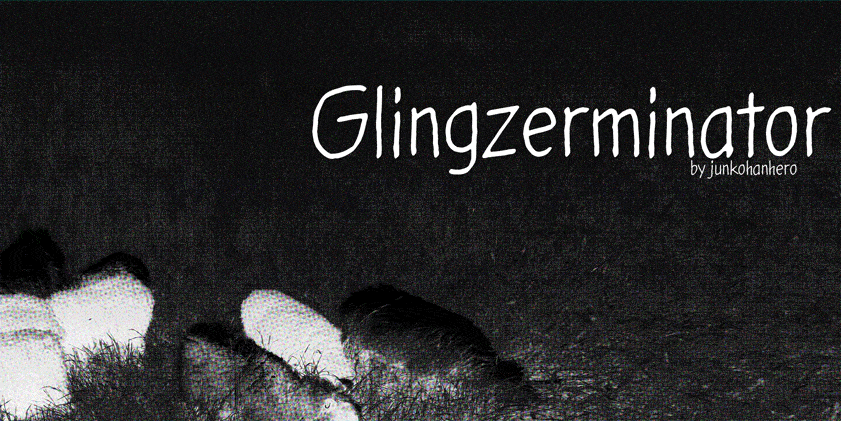
Glingzerminator Font
Aqui está uma versão em português do Brasil, envolvente e natural para a página de download da font “Glingzerminator”, escrita como se fosse um blog de recursos gráficos informativo: Nossa fonte Glingzerminator é um gênio brincalhão que não pode deixar sua sala de estar em paz. Especialmente criada para quem ama um pouco de humor nas páginas do seu projeto, essa fonte tem a capacidade única de fazer seu trabalho soar mais como uma divertida jogatina que um esforço sério. Se você está procurando por algo com o qual criar designs alegres e cheios de vida sem abrir mão de sua privacidade ou ser obrigado a pagar por isso, então Glingzerminator é definitivamente para você. É totalmente grátis para uso pessoal; só precisamos de um pouco mais de seu tempo para manter suas páginas engraçadas e coloridas. O designer Hamilton criou uma fonte que brinca com letras e ideias, transformando cada página em um divertido desafio de criação. Com ele, você pode manter o espírito da sua arte enquanto se divertindo a partir dos 15 euros e 20 dólares (ou qualquer outro valor equivalente) no sistema PayPal que Hamilton usará para apreciar seu trabalho. Glingzerminator é uma fonte de diversão na caixa, perfeita para aqueles desenhos onde cada palavra parece ter um rostinho pronto para estourar ao som da sua risada. Não importa se você está criando cartões de aniversário ou um mural inspirador, Glingzerminator é a fonte que o levará à próxima montanha arranhada do design.